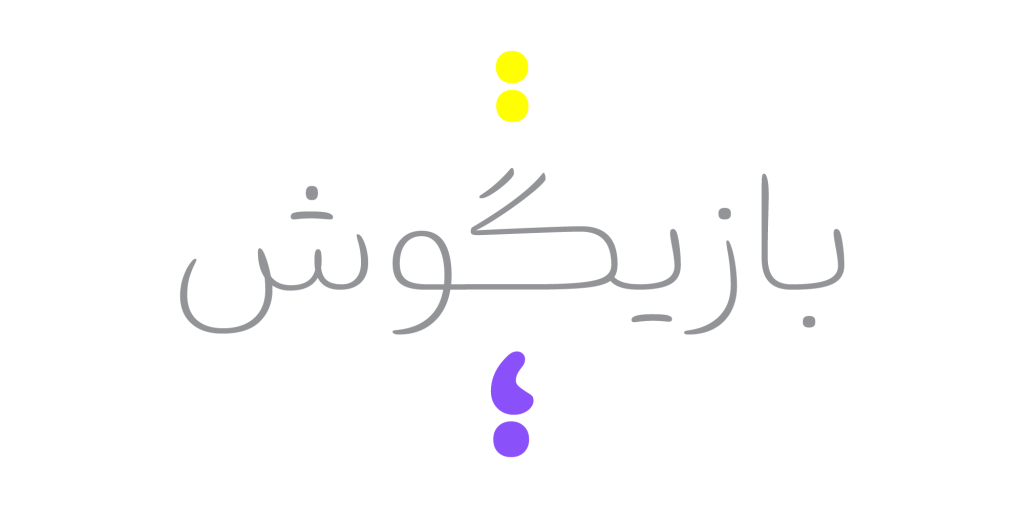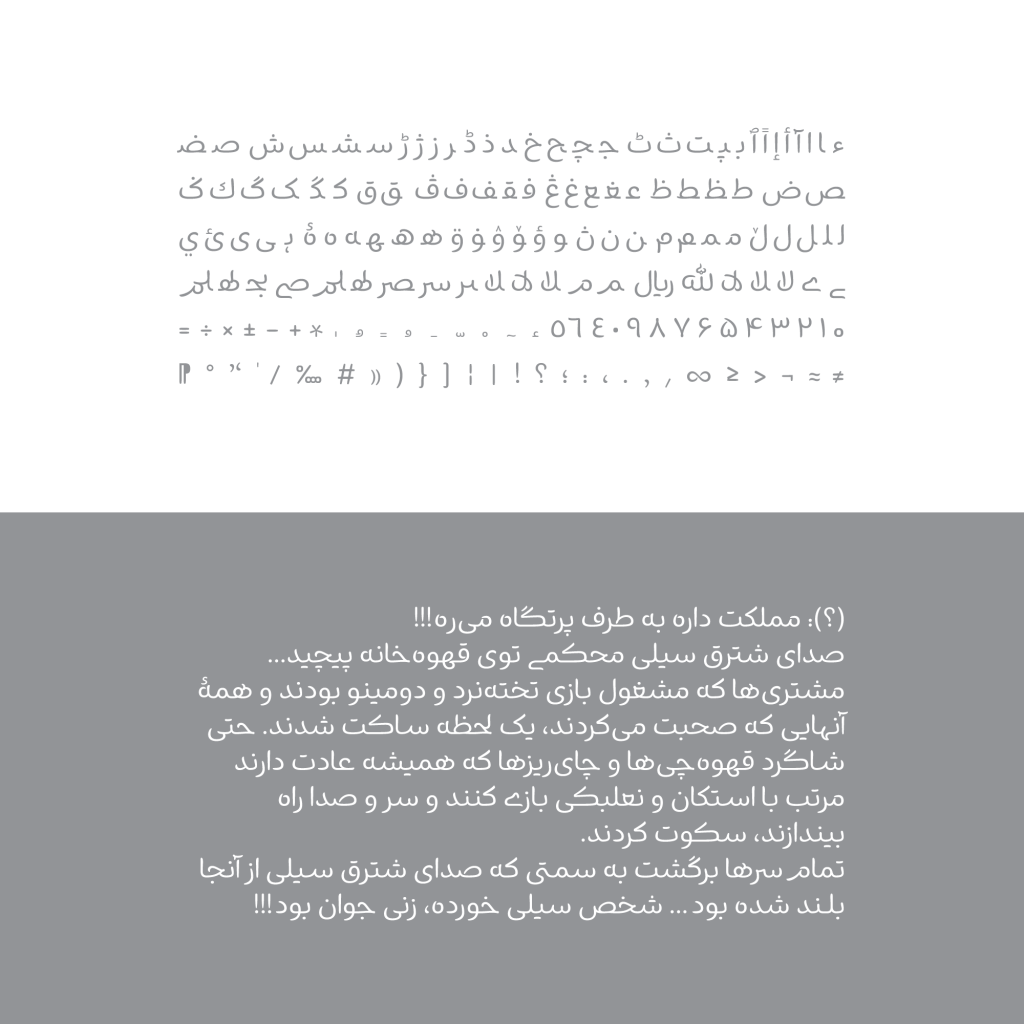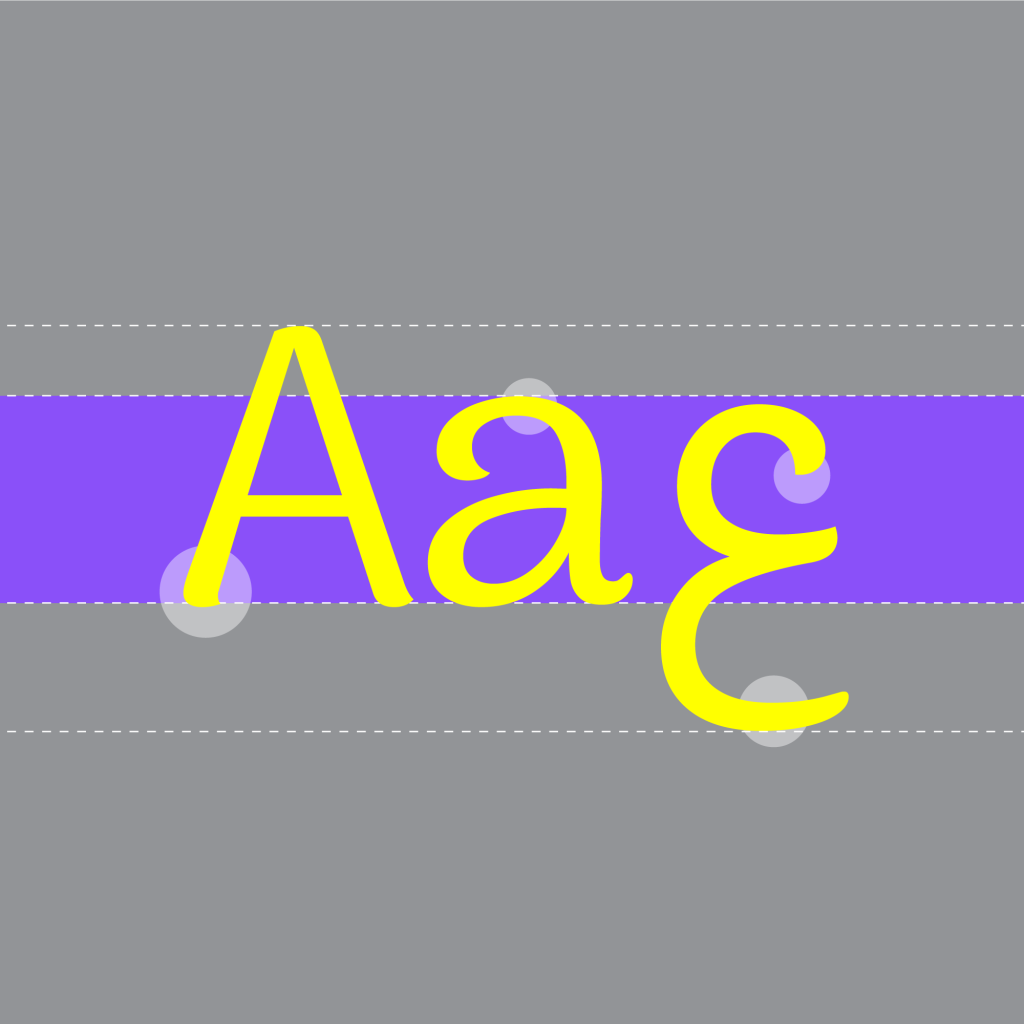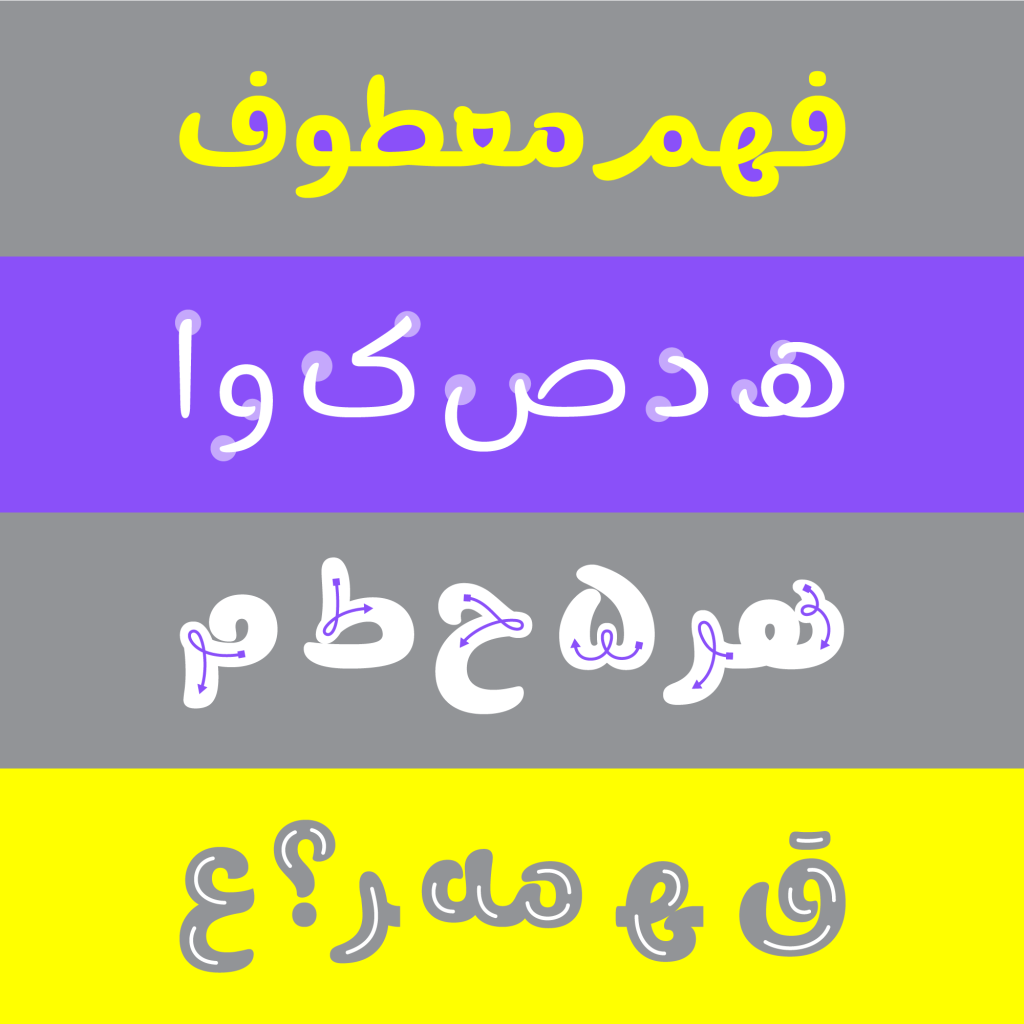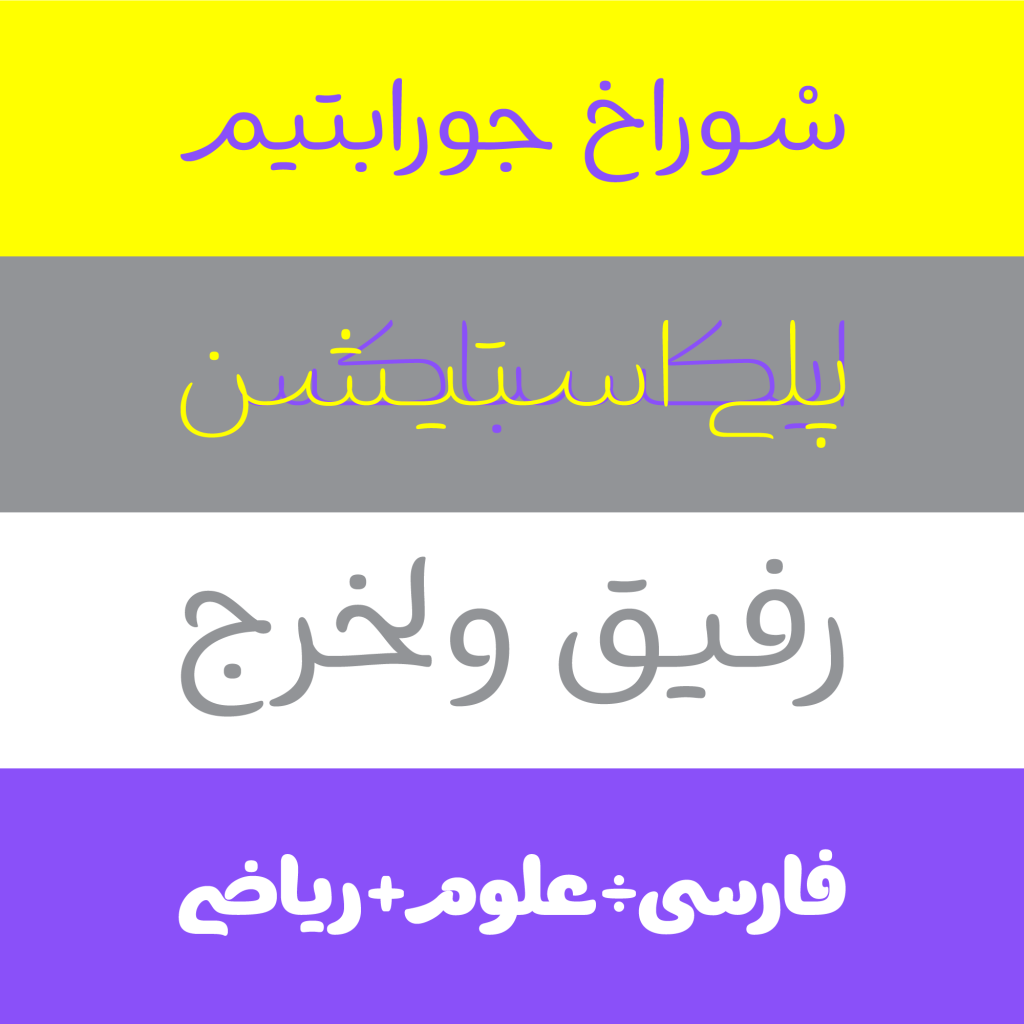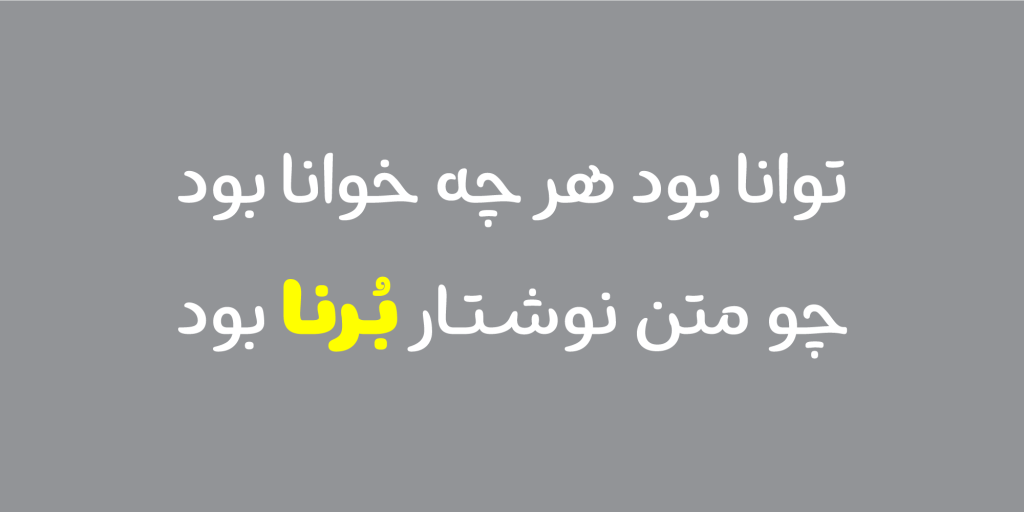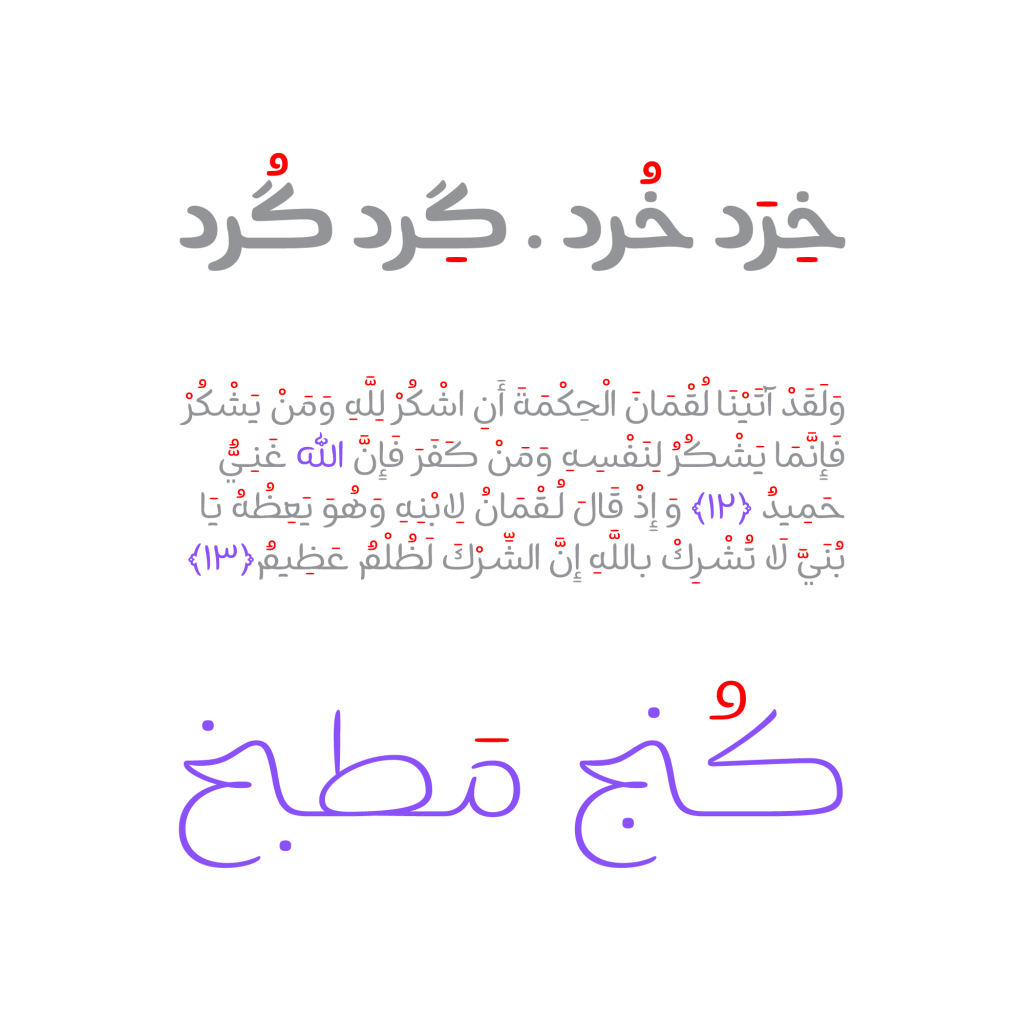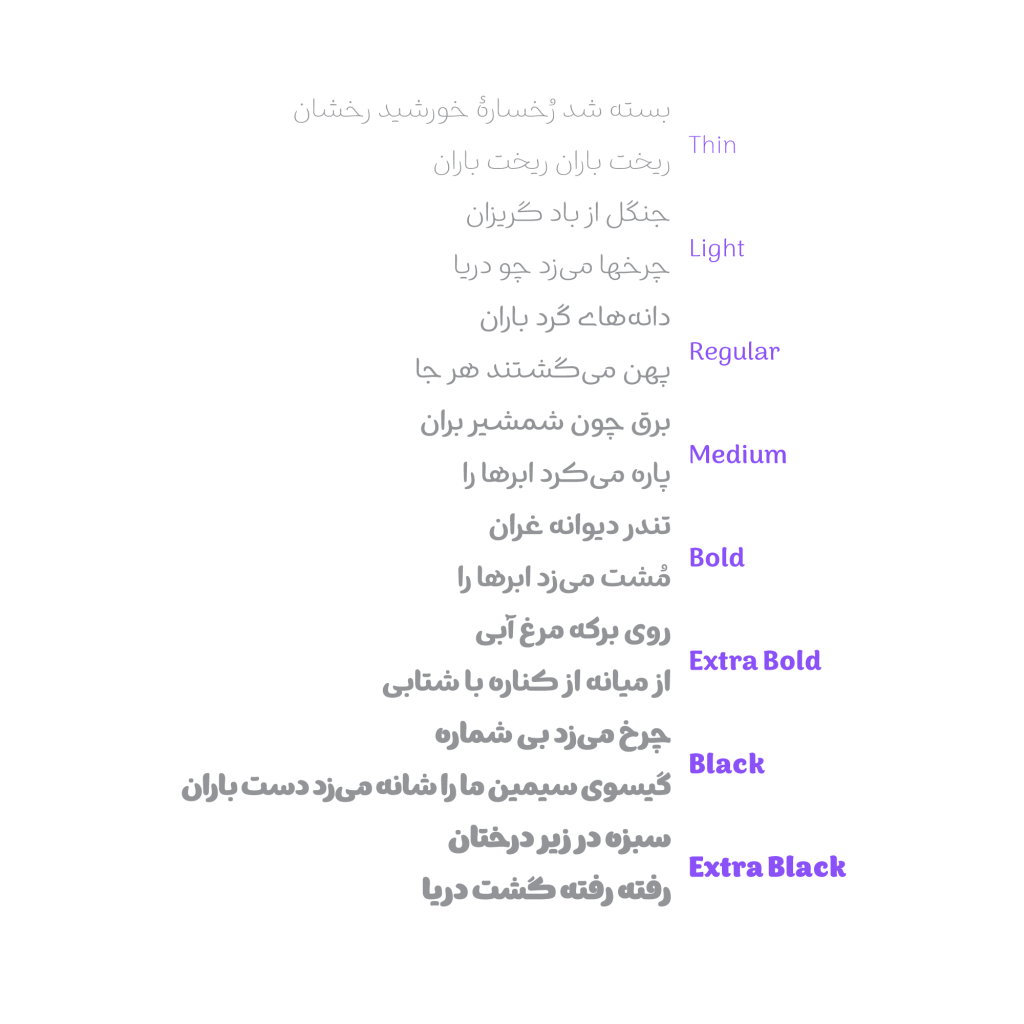
فونت برنا
فونت برنا تایپ فیسی از خانواده دست نویس است که اقتباسی از فرم های خط کوفی مغربی را در خود دارد. با دقت در این قلم مشاهده می کنید که فرم های سیال و روان پرتکرار در تار و پود برنا است. همچنین جست و خیز در دندانهها، چرخش در کاسهها، پیچ و تاب در فرمها و درشت بودن چشمها حس پویایی و جنب و جوش را به قلم داده همانند فونت ایران سنس دست نویس است.
خانواده برنا با بهره مند بودن از 8 وزن متفاوت از خیلی نازک تا خیلی ضخیم تنوع بی نظیری از وزن ها را در اختیار طراحان قرار می دهد. تا با باز گذاشتن دست طراحان در انتخاب وزن مورد نظر و دلخواه خود زیبایی دوچندانی به متون و نوشته ها افزوده گردد. علاوه بر این قلم برنا دارای نسخه متغییر و وریبل نیز است .
این قابلیت نو و جدید که تقریبا از سال 2016 به تایپ فیس ها و فونت ها افزوده شده بدین ترتیب است که تمامی وزن ها ، حالت های نقطه گذاری ، حروف و ترکیبات جایگزین ، کشیدگی ها و …. در یک فایل قرار داده شود که پر واضح است. سرعت بالاتر خصوصا در وبسایت ها به دلیل کاهش حجم و کاهش تعداد درخواست از سمت کلاینت به سرور از فواید این تکنولوژی جدید است.
این قلم مناسب فضای کودک و نوجوان است . کمی بازیگوش و پرانرژی می باشد . با روحیه شادی که دارد حس صمیمت و مهربانی را به مخاطبین و بییندگان منتقل می کند. می توان با استفاده از نرم فزار های طراحی از جمله آدوبی ایلسترتور و فتوشاپ از فونت برانا برای طراحی مجلات کتاب ها بروشور پوستر مقالات و پست های وب سایت ها و شبکه های اجتماعی و … با فضای شاد و پرانرژی بهره گرفت.
پشتیبانی برنا از ترکیبات جایگزین
برنا قلمی با روحیه به روز و امروزی و پرتلاش همه آنچه نیاز دارید را در دل خود دارد. طراحی فرمهای کشیده در برخی حروف و جایگزینهای پرکاربرد، ترکیبهای متنوعی را در اختیار طراحان قرار میدهد. در فایل راهنمای این محصول نحوه استفاده از این حروف جایگزین آموزش داده شده است. همچنین امکان تغییر رنگ در حرکتگذاری روی حروف کمک میکند تا عبارتها و جملات زیباتر به نظر برسند.